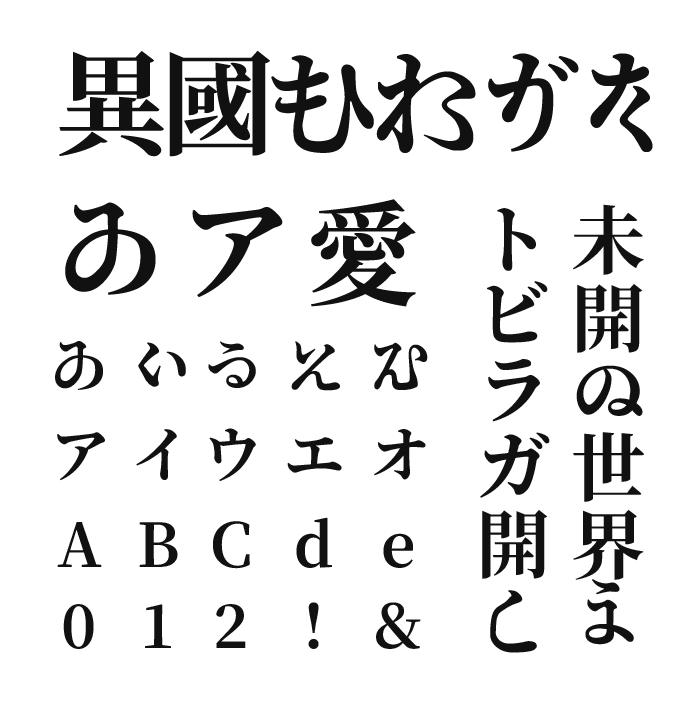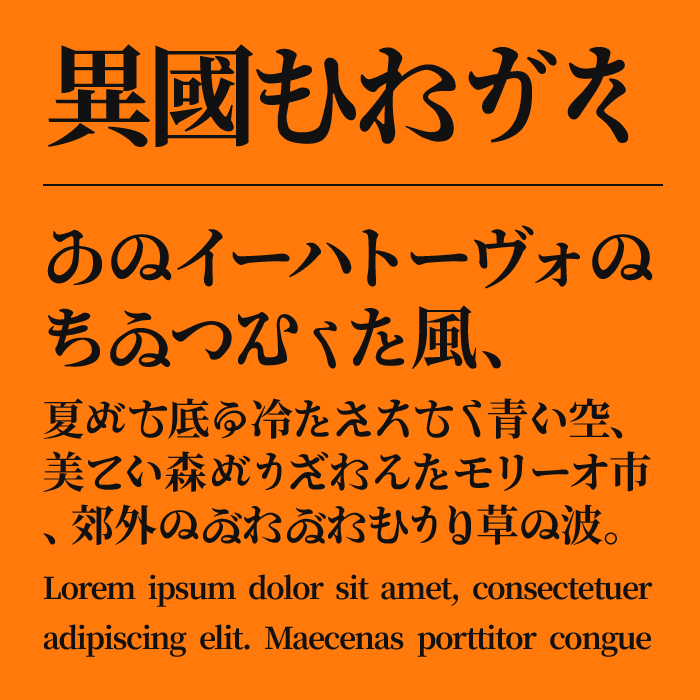
異國ひらがなは、昔の活字や古い読み物を思わせる形に、独特の丸みや揺らぎを加えた異国感のあるフォントです。
漢字は明朝体らしい端正さを持ちながら、ひらがなになると筆で流れるような線が増え、文字によって表情が大きく変わります。
大正から昭和初期の広告、古書、映画のタイトルなどを思わせる雰囲気があり、和風デザインの中でも少し妖しさや物語性を加えたいときによく合います。小説や文学作品のタイトル、和菓子や日本酒のパッケージ、レトロなポスターなどにも使ってみたくなるフォントです。きれいに整った明朝体とは違い、どこか異国めいた不思議な空気を感じさせます。
収録文字は、漢字・ひらがな・カタカナ・アルファベット・数字・記号が収録。